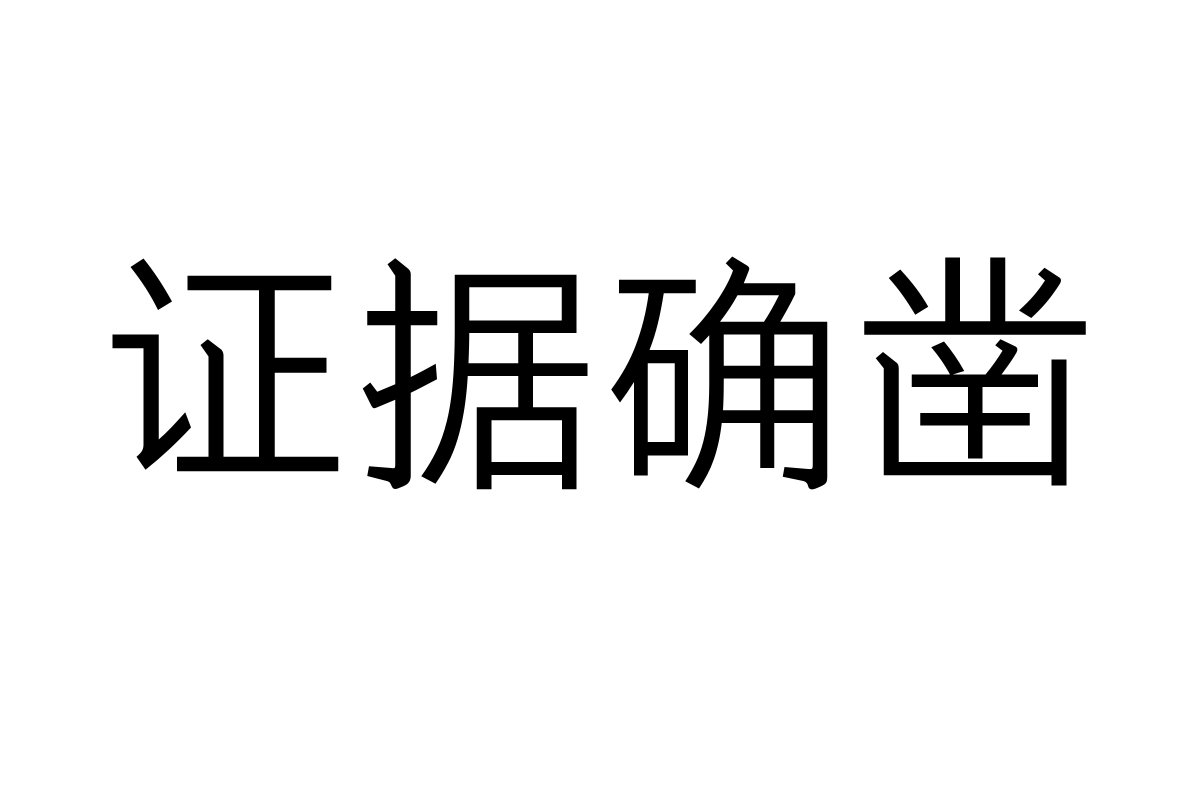
**汉仪铁线黑-45是一款具有现代感和艺术性的中文字体,广泛应用于各类书刊、画册、包装设计以及字体设计中**。
这款字体以其独特的线条与圆弧组合,展现出一种稳定而可靠的感觉。这种直线与圆弧的结合,不仅使字体的视觉效果更加独特,也赋予了其强烈的视觉冲击力。同时,汉仪铁线黑-45简字体的笔画粗细均匀且字符间距平衡,使得整个字体看起来非常稳定。
该字体在广告设计、宣传海报、PPT制作、影视制作等领域有着广泛的用途。由于其个性鲜明,可以适用于任何需要文字表达的场景。此外,汉仪铁线黑-45简字体还支持TrueType格式,这意味着它能够与各种软件兼容,便于设计师进行创作和编辑。
总的来说,汉仪铁线黑-45简字体以其独特的艺术风格和广泛的应用范围,成为了设计师们不可或缺的字体之一。无论是用于书籍封面还是网页设计,这款字体都能够为作品增添一份独特的魅力。